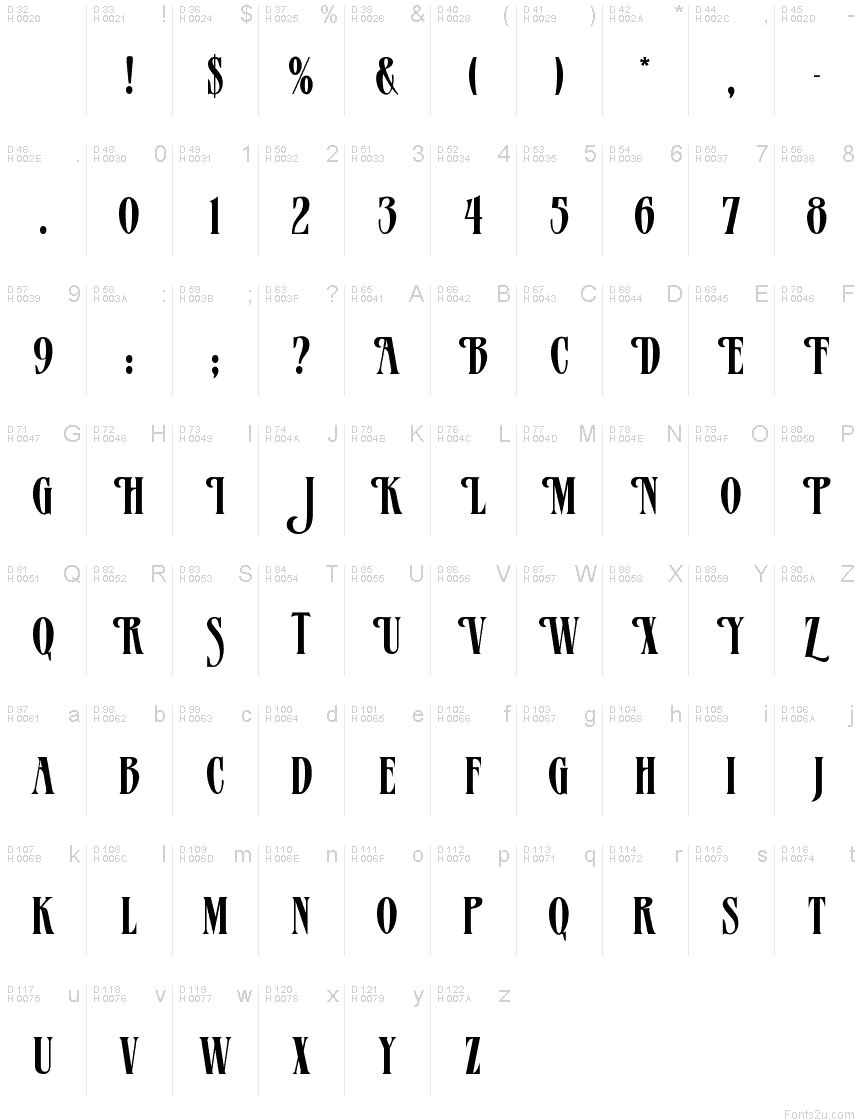
Mazama autorstwa Jamesa M. Harrisa to bezpłatny, retro-stylowy krój ekranowy, wyróżniający się wysoką, zwężaną sylwetką i ostrymi, skierowanymi do wewnątrz łukami, dzięki którym litery sprawiają wrażenie wyżłobionych, a nie luźno naszkicowanych. Powtarzalny rytm tych smukłych form nadaje projektowi formalny charakter — wystarczająco wyrazisty, by przywoływać na myśl plakaty w starym stylu czy tytuły książek, ale bez zbędnej dekoracyjności.
Taki kształt sprawdza się w nagłówkach, początkach rozdziałów, okładkach albumów, identyfikacji wizualnej restauracji czy plakatach wydarzeń, gdzie wąska, pionowa tekstura stanowi główny element wizualny. Szczególnie krótkie nagłówki zyskują na tej dynamicznej formie, która nawet prostym słowom nadaje ceremonialną obecność i wyraźnie vintage'owy sznyt.